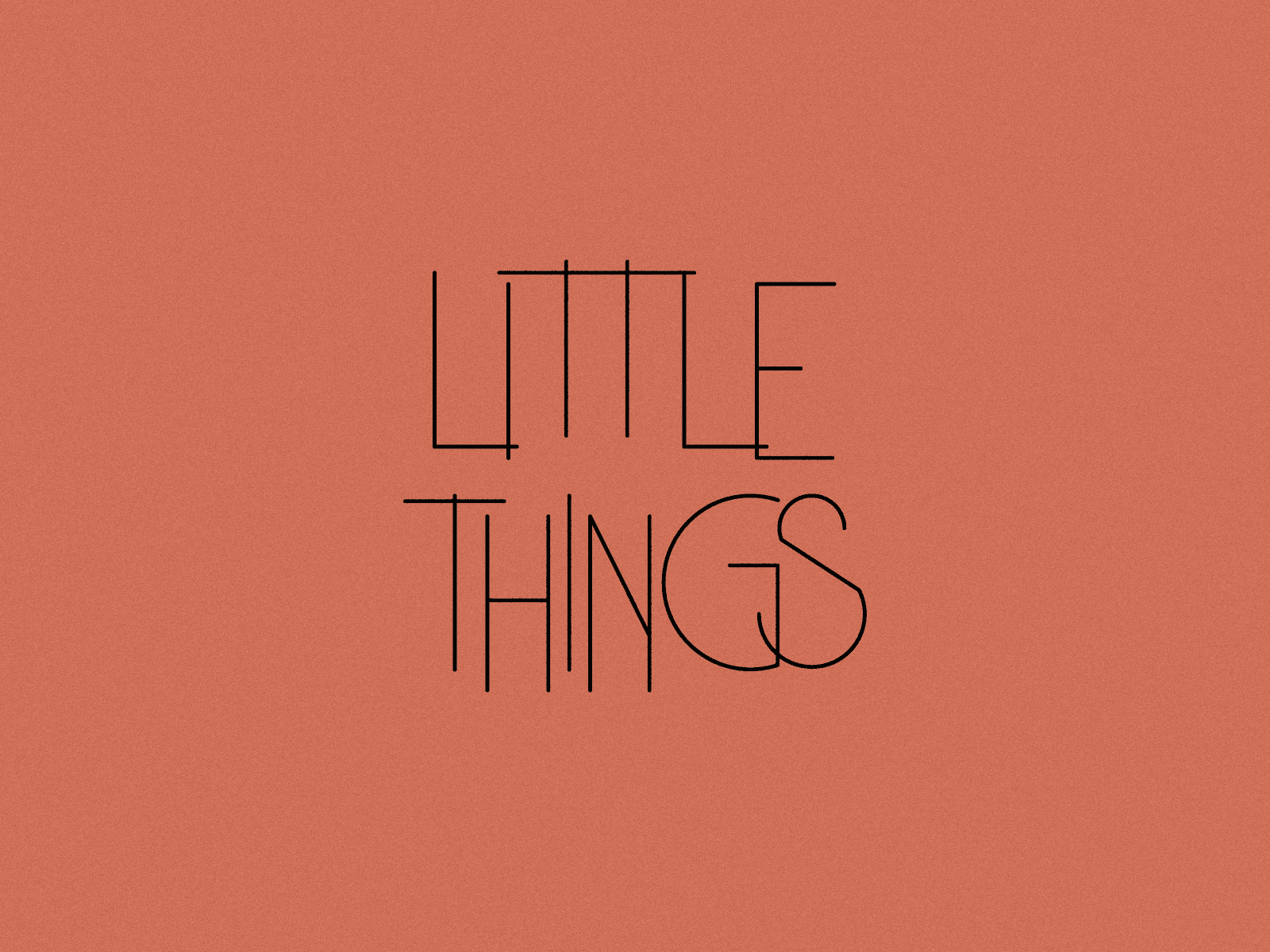
Estudo tipografia
Estudo de tipografia (com e sem serifa) a partir de linhas simples. . Study of typography (serif and sans serif) using simple lines.